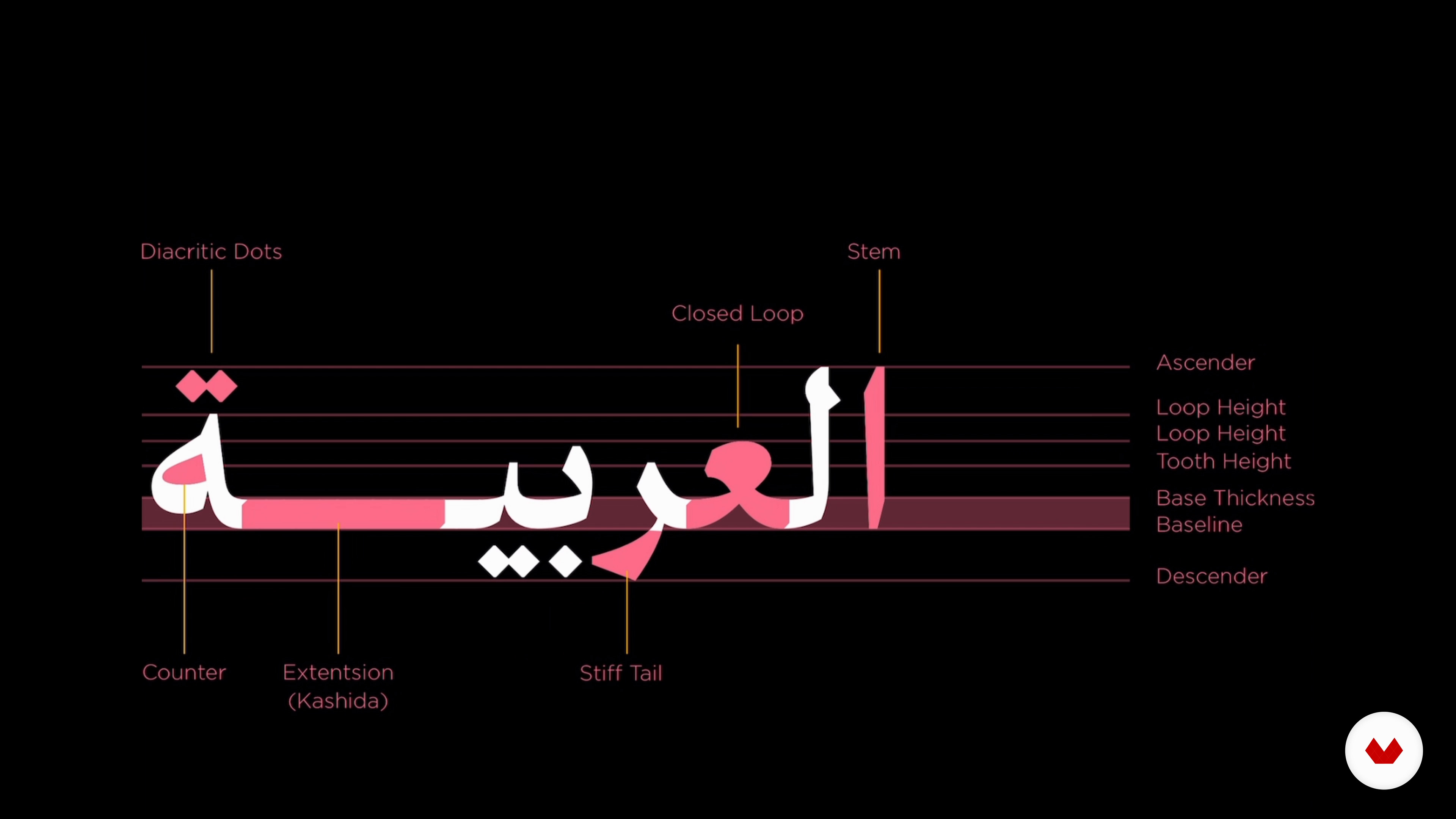
Typografia arabska: Style anatomiczne
O lekcji wideo: Typografia arabska: Style anatomiczne
“W tej lekcji poznamy anatomię liter arabskich, zrozumiemy wytyczne: linia górna, wysokość pętli, wysokość zębów, linia bazowa, linia opadająca. anatomia liter (łodyga, ząb, ramię, jelito, głowa, sztywny ogon, pętla, ucho igły, żebro) dowiedz się, jak można łączyć ze sobą pisma łacińskie i arabskie, jak to zrobić i czego unikać. ”
Na tej lekcji wideo Kinda Ghannoum porusza temat: Typografia arabska: Style anatomiczne, która stanowi część kursu na platformie Domestika: Dwujęzyczne tworzenie marki z arabskimi znakami. Opanuj podstawy projektowania międzykulturowego i zgłębiaj typografię arabską. Od wstępnych badań i szkiców po prezentację dla klienta i publikację..
“W w tej lekcji zajmiemy się trochę kształtami liter i omówimy kwestie związane z dobieraniem par Typografia arabska i łacińska. Czcionka arabska ma taką samą anatomię jak czcionka łacińska. Posiada również ramiona i trzony szeryfowe. Niezależnie od tego, czy jesteś początkującym projektantem, czy po prostu lubisz typografię, Poznanie podstawowych zasad typografii pomoże Ci w jej skuteczniejszym stosowaniu. Część tego, co zamierzam powiedzieć, może wydawać się zbędna, zwłaszcza jeśli już potrafisz pisać po arabsku. Jednakże, nawet jeśli jesteś z tym zaznajomiony, możesz popełnić błędy projek...”